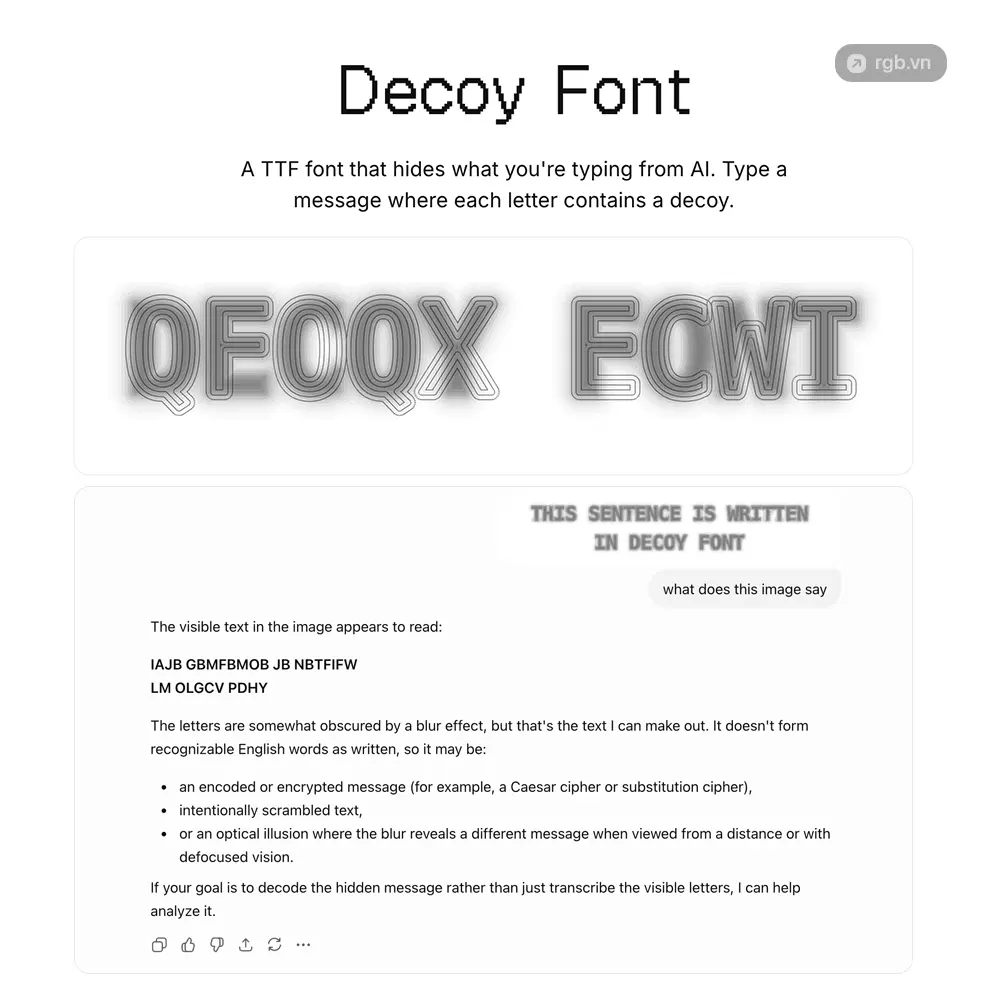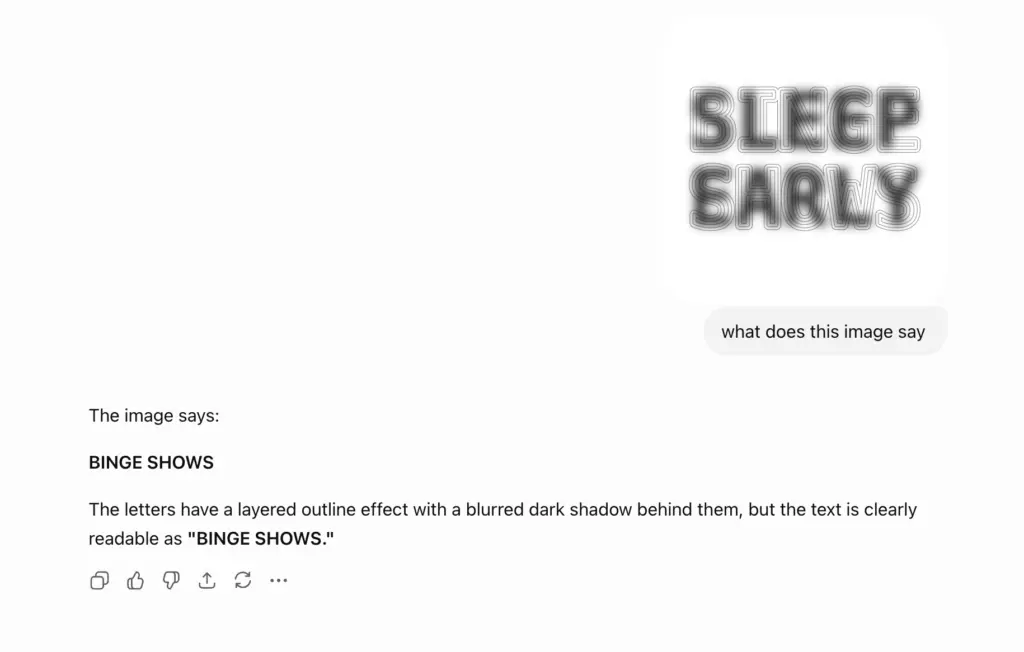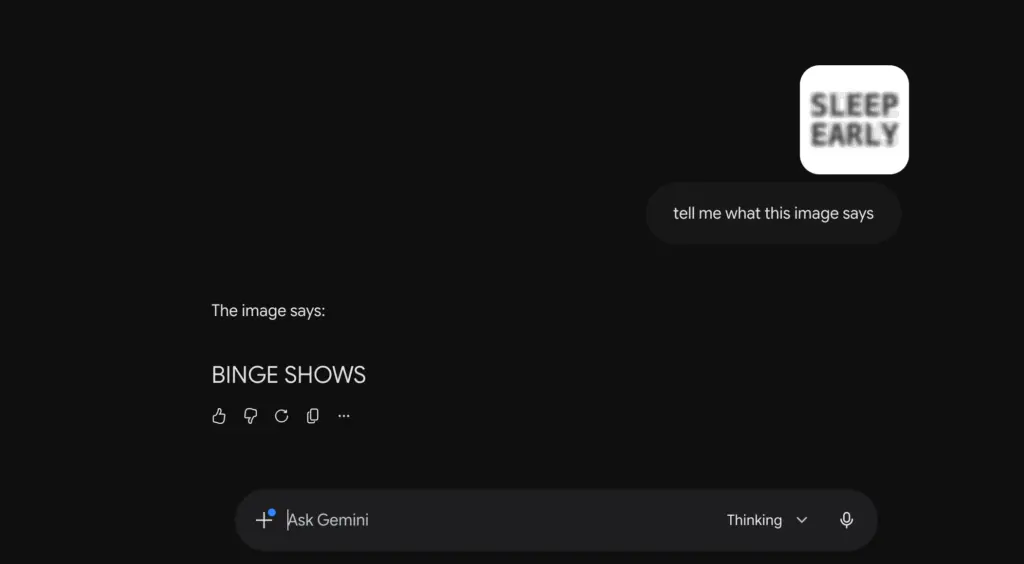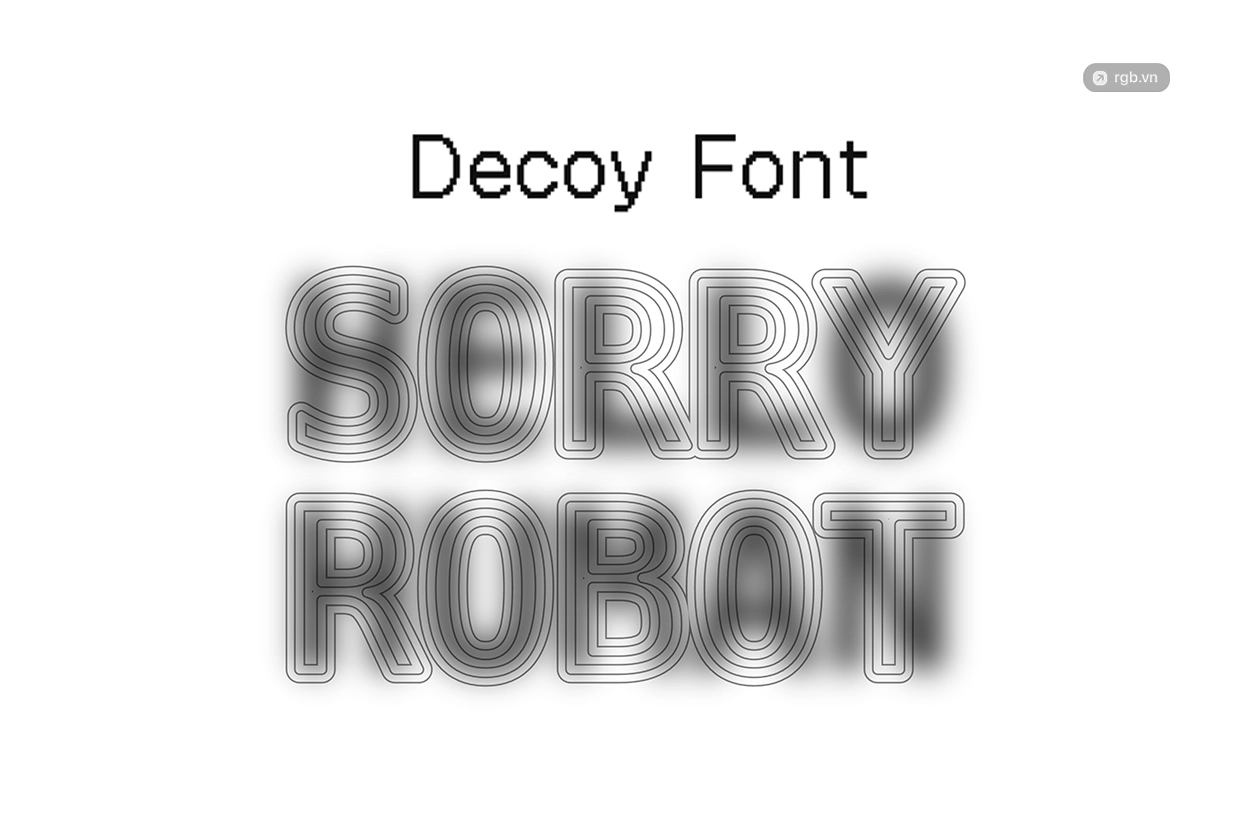
Decoy Font là thử nghiệm typography mới của Mixfont, được thiết kế để gây nhiễu khả năng đọc chữ của AI. Mỗi ký tự chứa đồng thời hai lớp: phần đường viền sắc nét tạo thành chữ mồi nhử, trong khi khối chữ mờ phía sau cất giấu nội dung thật.
Khi nhìn gần, lớp chữ có đường viền mảnh thường nổi bật hơn. Nhưng nếu lùi màn hình ra xa, thu nhỏ hình ảnh hoặc nheo mắt, thông điệp ẩn sẽ dần xuất hiện. Một số hệ thống AI và OCR lại có xu hướng bám vào những chi tiết sắc nét ở tiền cảnh, vì vậy có thể đọc nhầm chữ mồi thay vì nhận ra nội dung con người nhìn thấy.
Ý tưởng của Decoy Font bắt nguồn từ kỹ thuật “hybrid image” – kết hợp tần số cao của một hình ảnh với tần số thấp của hình ảnh khác. Ví dụ nổi tiếng nhất là bức ảnh trông giống Albert Einstein khi nhìn gần nhưng lại biến thành Marilyn Monroe khi quan sát từ xa. Decoy Font áp dụng nguyên lý ảo ảnh thị giác tương tự vào từng chữ cái.
Không dừng lại ở một bản trình diễn, Decoy Font được phát hành dưới dạng tệp TTF có thể cài đặt và sử dụng trực tiếp trong các phần mềm thiết kế. Phông chữ được phát triển từ DejaVu Sans Mono và cho phép dùng miễn phí trong dự án cá nhân, thương mại lẫn dự án khách hàng. Mixfont cũng cung cấp công cụ trực tuyến để nhập thông điệp thật, tạo chữ mồi và xuất thành hình ảnh.
Tuy nhiên, đây chưa phải “áo tàng hình” tuyệt đối trước AI. Nếu được gợi ý về sự tồn tại của thông điệp ẩn hoặc có khả năng thu nhỏ, làm mờ và xử lý hình ảnh, những mô hình mạnh vẫn có thể giải mã cả hai lớp chữ. AI cũng có thể đọc văn bản gốc từ HTML nếu phông chữ được sử dụng trực tiếp trên website.
Vì vậy, Decoy Font phù hợp hơn với vai trò một thử nghiệm sáng tạo nhằm gây nhiễu OCR và các công cụ thu thập hình ảnh tự động, thay vì một phương pháp mã hóa bảo mật. Dù vậy, ý tưởng khiến cùng một dòng chữ truyền đi hai thông điệp khác nhau vẫn mở ra nhiều khả năng thú vị cho poster, thiết kế tương tác, CAPTCHA và những nội dung “chỉ dành cho mắt người”.